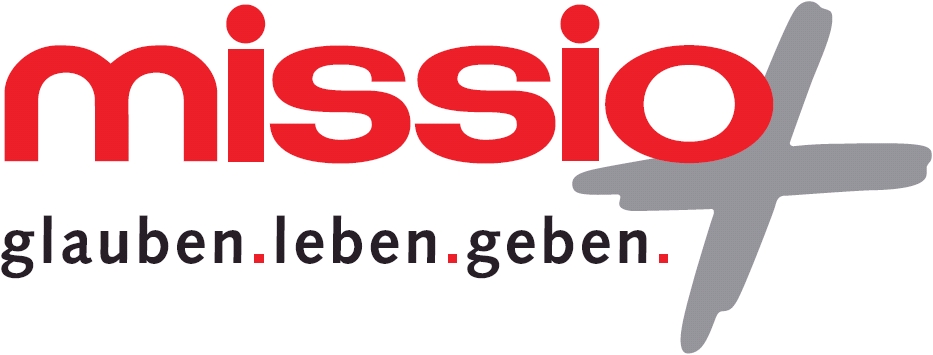
Aus welche Schriften mag das gebastelt sein?
Es geht nur um "missio" … kennt ihr Schriften, die irgendeine Gemeinsamkeit haben oder ist das alles handgebissen?
Das "s" ist ja ganz sauber konstruiert:
Das ist du Syntax, ja. Aber wo könnte so ein s vorkommen? Es wird wie das in die Breite gezerrt worden sein …
Ich glaube ja auch, dass sich handwerklich ordentliche Konstruktion und ungeschickte Gestaltung prinzipiell nicht ausschließen ... Meine Vermutung: Da sind Elemente verschiedener Schriften im Illustrator zusammengerührt worden, das würde dann zum Einen die verschiedene Breiten der Senkrechten und zum Anderen auch die sauberen Ankerpunkte erklären.
EDIT: s und o sieht für mich auch wie eine nachträglich gedehnte Univers (2-fach extd.) aus. Die i sind wohl einfach aus Rechteck und Kreis gebastelt und das m: 2 gespiegelte, gedrehte u?
Mit Illustrator hat das aber bestimmt weniger zu tun. Ist das nicht auch schon voll alt? 70er? Da gab es Illustrator nur als Beruf. ?
In den 70ern waren die Linienbreiten  von s und o noch ausgeglichen, die i hatten eckige Punkte, das ganze Logo war kompress. Im Zeitalter der Säurebadfarbkorrektur wurden Reinzeichnungen ... nun ja, gezeichnet. Die Frage war aber, ob die saubere Vektorzeichnung eventuell teilweise auf einem bestehenden Font basieren könnte. Und je nachdem, wann das jemand vektorisiert hat, kann er/sie es selbstredend auch mit GEM Graphics, Corel Draw, Freehand o. ä. gemacht haben.